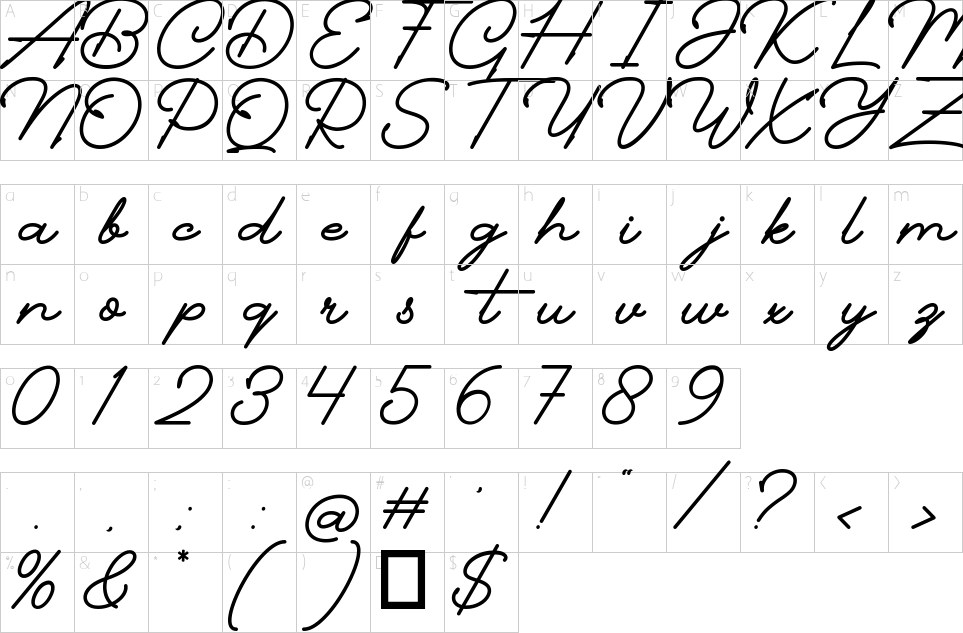
Descubra a fonte Pethafis, um belo complemento para suas criações digitais. Desenvolvida pela RGB Studio, esta fonte é uma escolha ideal para designers que buscam uma grã-expressão e uma personalidade única. Com seu design criativo e vibrante, Pethafis oferece uma série de opções de estilo que podem adaptar-se a uma ampla gama de projetos. Esta fonte foi projetada para Windows e Mac, facilitando a integração em qualquer ambiente de trabalho digital. Com uma variedade de caracteres e uma aparência elegante, Pethafis é perfeito para gráficos, logotipos e outros elementos visuais que exijam um toque especial. Com 776 downloads já registrados, você pode começar a experimentar esta fonte imediatamente. Não deixe de experimentar Pethafis para adicionar um toque único e atraente a seus projetos digitais.